今回は縦画・横画の太さによる視覚調整のポイントを紹介します。
今回の記事で紹介する縦画・横画は、「下ほど太く」「右ほど太く」というルールに沿って制作することが多い例です。これも前回記事の空き部分と同様で、人の目には上部が膨張して見えるためです。
横画の多い「圭」を例に挙げて紹介します。横画の太さや、横画の間の広さを均一にしてしまうと、上側の「土」の方が大きく見えてしまいます。
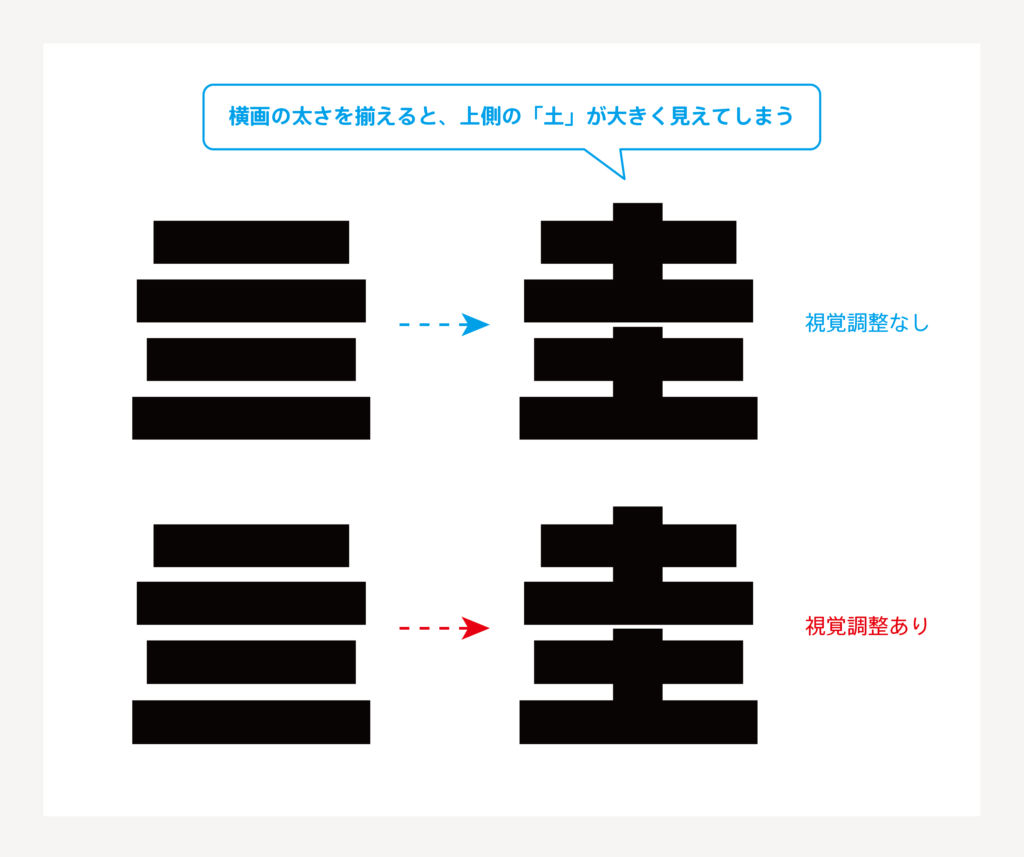
「田」や「圭」は直線の縦画・横画だけで構成されていて、左右対称のシンプルな形をしていますが、それぞれの線の太さや配置は、機械的に決まっているわけではありません。「右側・下側ほど太く、広く」といった視覚調整に則って、人の目にどう見えるかを考えて制作されています。